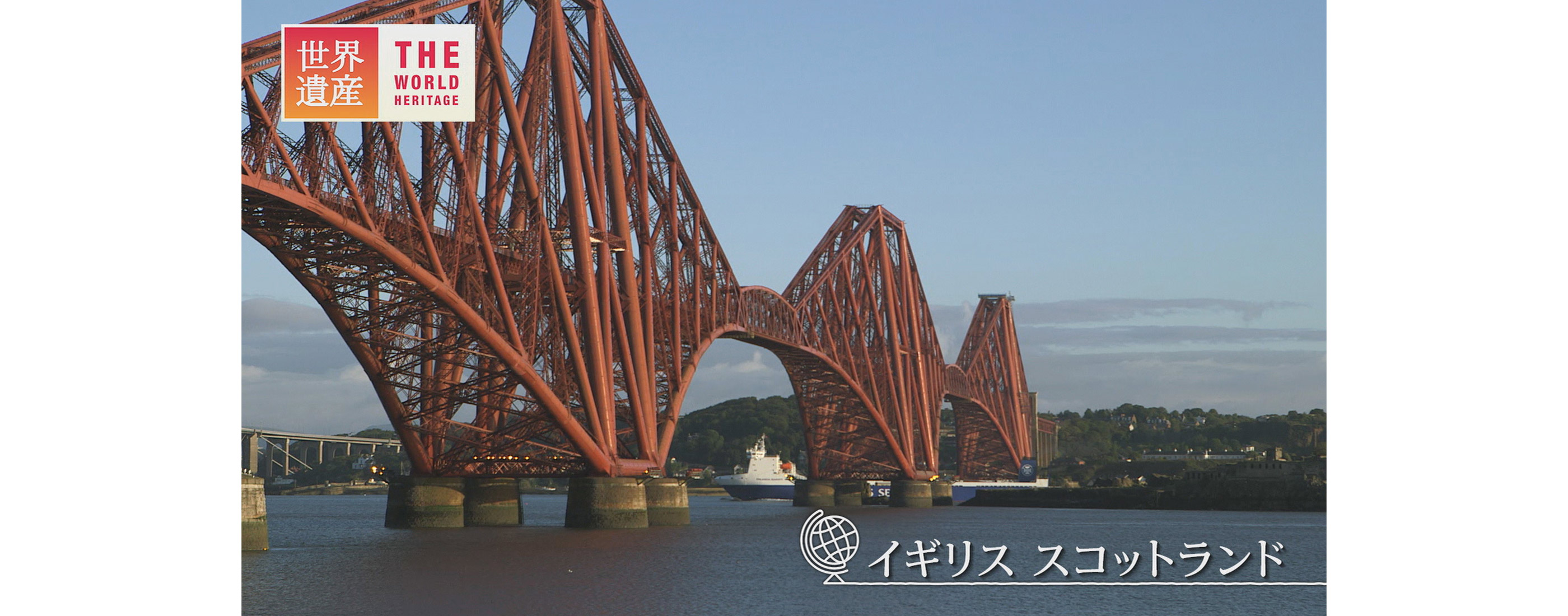
世界遺産と共存する明朝体
TBS テレビで毎週日曜午後6 時から放送されている「世界遺産」。「過去から引き継がれてきた地球や人類の歴史を未来へ繋げていこう」という世界遺産の精神に寄り添いつつ歩んできたこの番組は、2015 年4 月、放送開始から20 年目を迎えるにあたってリニューアルを行い、テロップの書体として新たにTP 明朝を採用しました。
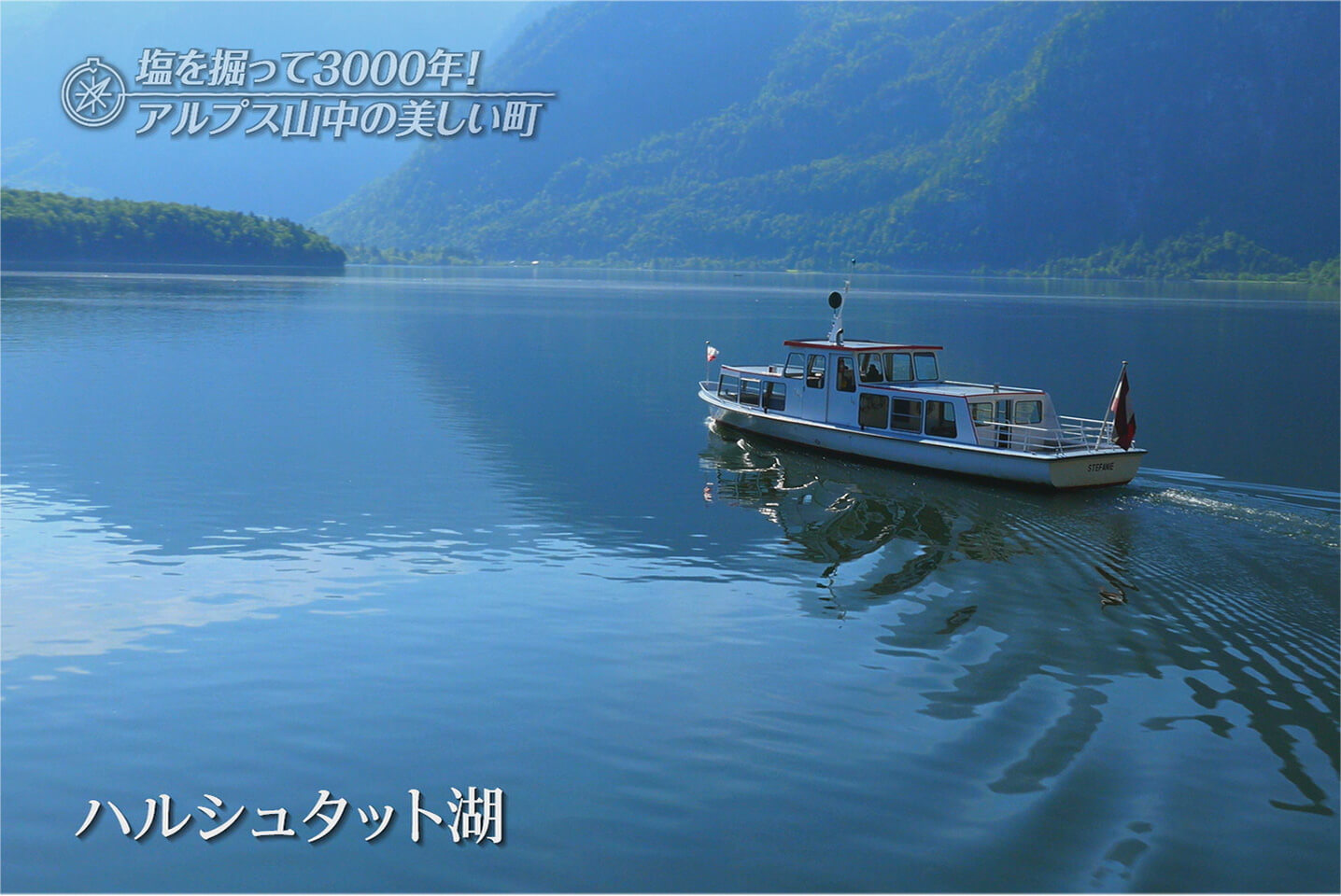
TP 明朝を選んだ経緯について、「世界遺産」の制作を担当している株式会社TBS ビジョンのディレクター、大矢慎吾氏は次のように語っています。「まず、世界遺産、すなわち世界のさまざまな自然や文化を語る文字としては、普遍性につながる書体である明朝体がいいのではないかという思いがありました。また、映像が主役の番組ですから、文字には自己主張が強すぎない、なるべく透明な印象のフォントが望ましい。そして何より、映像に文字を重ねたときの読みやすさが重要でした。番組のリニューアルに際して『こういうイメージのフォントがいいなあ』というような話をしていたとき、CG デザイナーから提案されたのがTP 明朝です。『なるほどこれはきれいだな』というのが第一印象でした」
TP 明朝は、デジタル環境での読みやすさを追求し、横組みに最適化した書体設計をおこなった明朝体です。ウエイトに加えてコントラスト(横画と縦画の太さの比率)という軸を導入することで、幅広いシーンにおいて環境に応じた選択を可能としました。また、TP 明朝の現代的な筆画表現と文字骨格は、斜体などの変形をかけた使い方にも適しています。
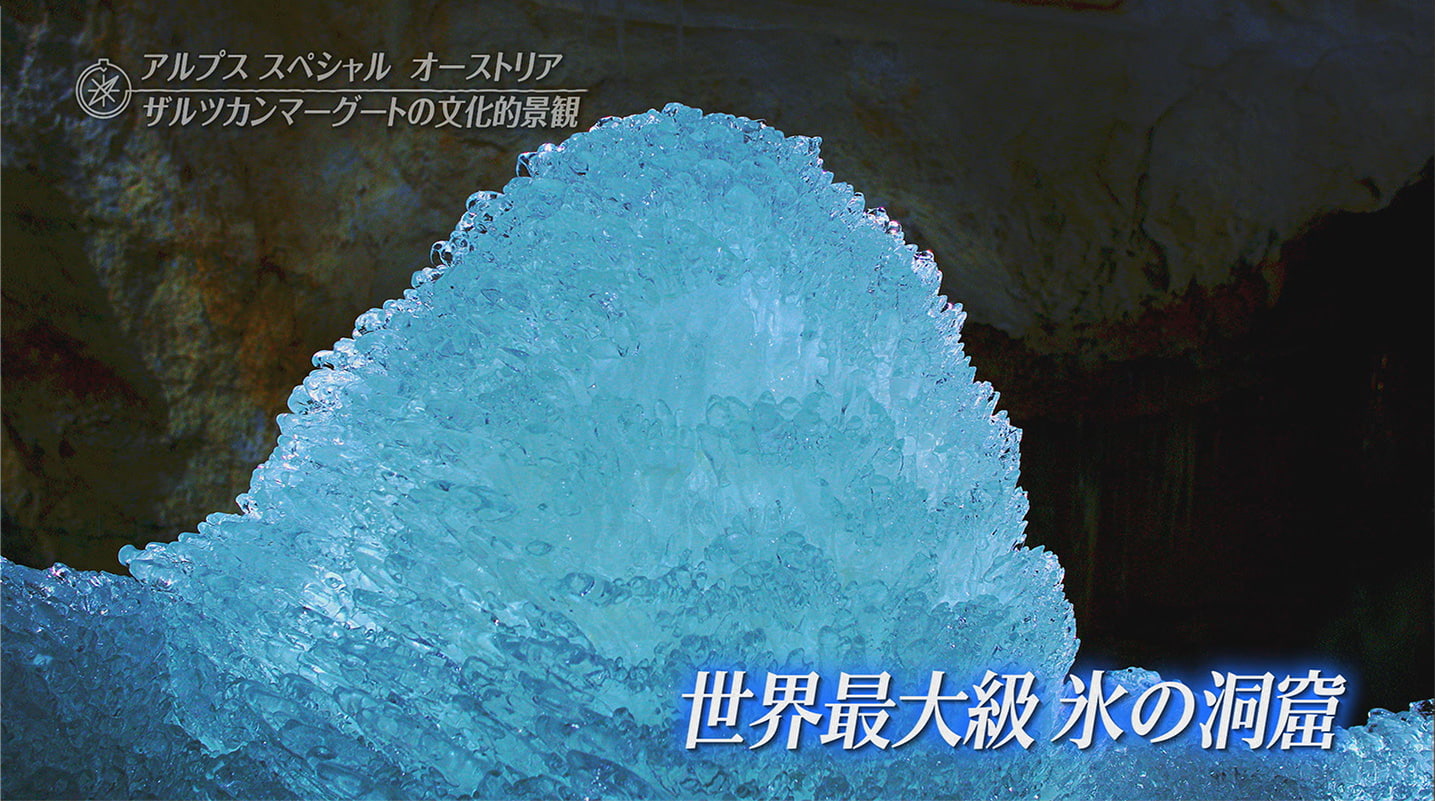
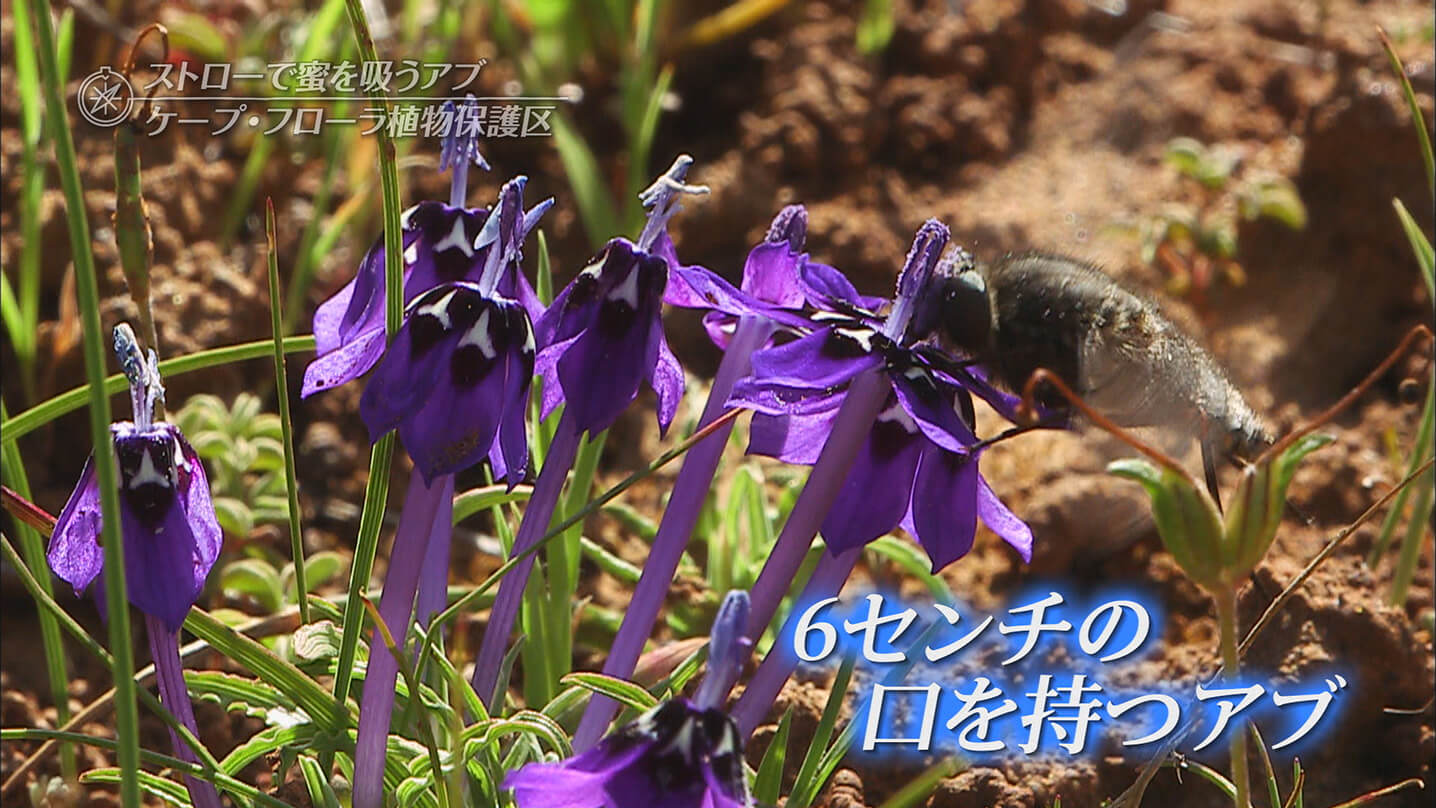
「番組にテロップを入れる場合、フォントはVTR を編集する段階で選ぶことが多いのですが、『世界遺産』では番組内での統一感を大切に考えて、ひとつのフォントをメインで使うという方針を貫いています。ですから、リニューアルの際のフォント選びは慎重におこないました。最終的には4 つか5 つの候補に絞って、これまでに放送した映像に文字を入れてみて比較検討した上で決定しました」
「世界遺産」では、テロップの文字はあまり大きくはありません。そのような使い方において横画が飛ばずに読みやすいこと、和文と英文のバランスがいいこと、細かい調整なしできれいに使えることなどから、大矢氏はTP 明朝のミドルコントラストを選びました。「最終的にTP明朝を提案したところ、プロデューサーもこのフォントを知っていて、『あれならいいね』と、スムーズに導入が決まりました。世界遺産という番組のイメージについては、スタッフのなかで共通のものができあがっていたのだと思います」
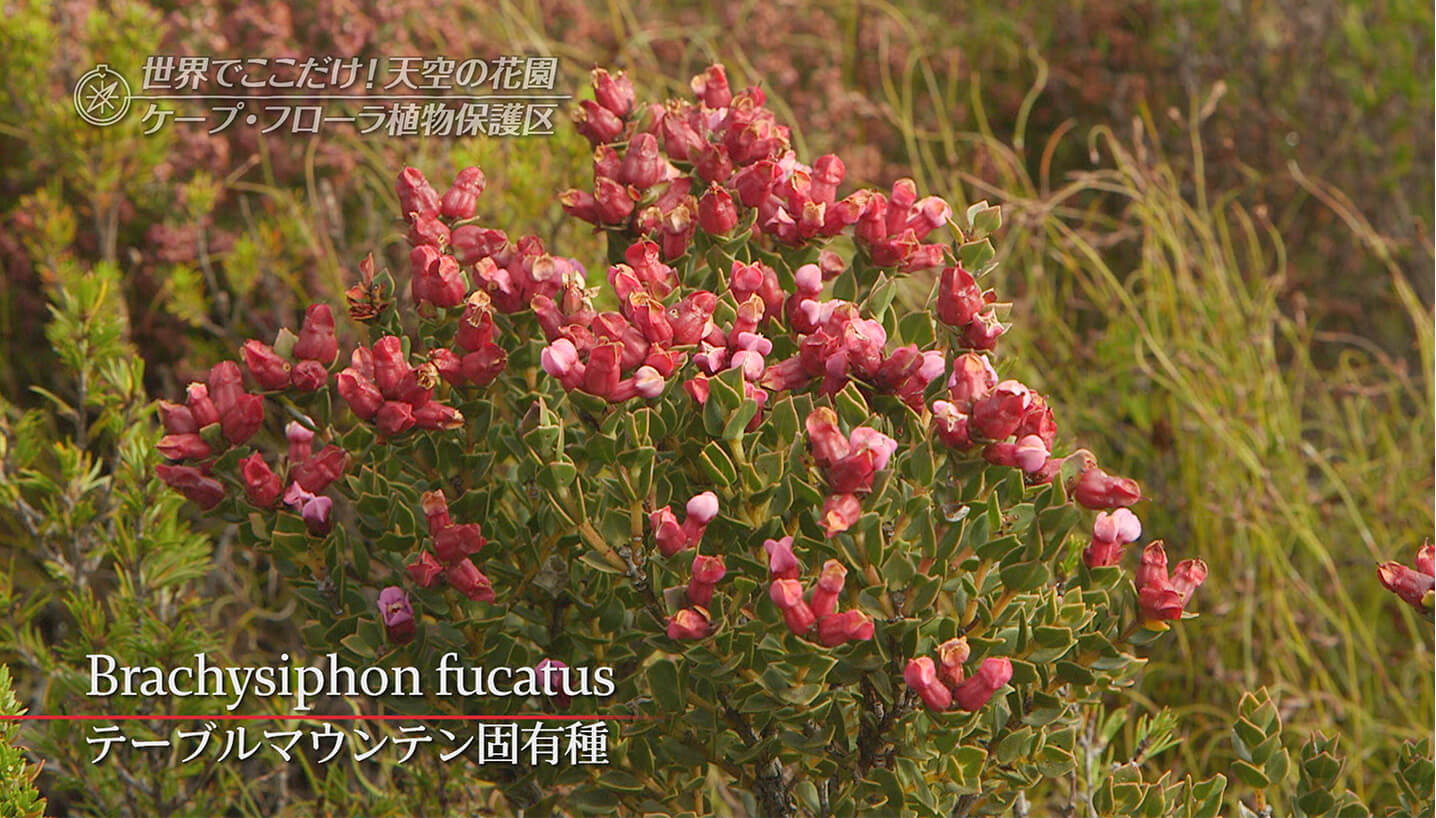
「世界遺産のおもしろさを、なるべく加工することなく届けたい。だから、文字の処理も最低限にしていて、そのぶんごまかしが利きません。たとえばどんな書体でも、何重にもエッジをつけるなどの処理をおこなえば、それなりに読みやすくなったりはするのですが、そうではなく、フォントのデザインのままできれいに見えてほしいし、TP 明朝はこの要求に応えてくれました。30 分という長さの番組のなかで、ちいさなお子様からご高齢の方まで、いろいろな人に世界遺産の魅力を味わってもらい、「そこに行ってみたい」と思ってもらえればうれしいですね。